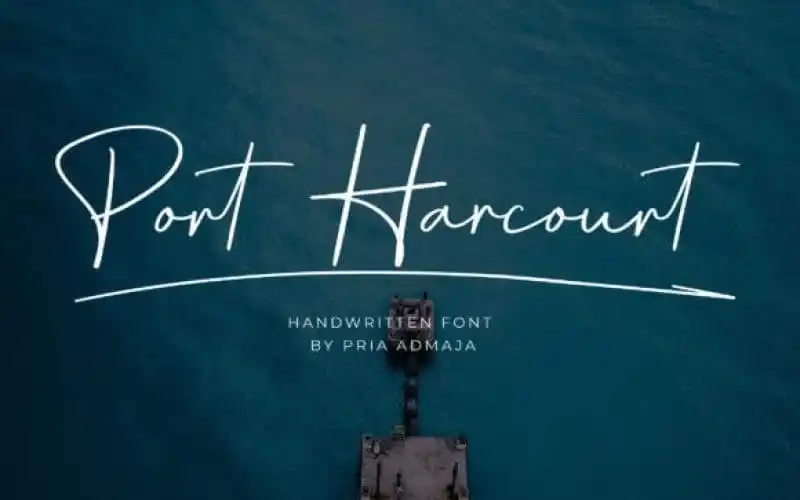
Port Harcourt Handwritten Font
A Port Harcourt Handwritten Font é uma seleção única de letras cursivas com muitas ligaturas que foram retiradas diretamente de verdadeiros traços manuscritos. Essas ligaturas, criadas pela Pria Admaja, proporcionam um resultado super natural aos inscrições, ilustrando o poder da arte do handwriting. Esta fonte é perfeita para adicionar um toque elegante e sofisticado em uma variedade de projetos, desde as cartas de agradecimento até os desenhos empresariais, trazendo ao design um toque autêntico e único. Seja no seu casamento, seus convites de agradecimento ou suas citações, essa fonte é perfeita para qualquer projeto que busque uma mão escrita aparente. Ela traz um ar elegante e encantador aos seus trabalhos gráficos.